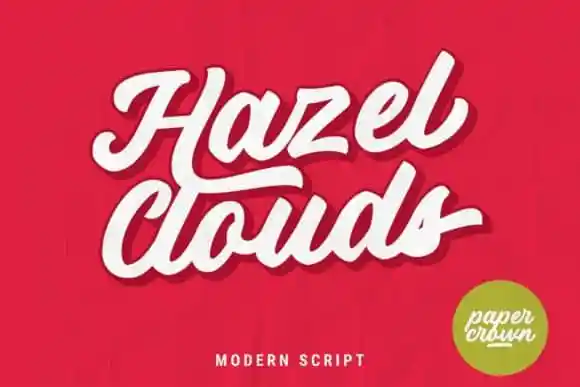
A Hazel Clouds Script Font é uma seleção única de letras decorativas que surgiu do cruzamento entre a arte manual de letra escrita e a tipografia. Feitas à mão, estas letras são perfeitas para quem busca um estilo elegante e sofisticado em suas criações digitais. Elas permitem criar textos fluidos e artísticos, idealmente para anúncios ou design gráfico que exija uma escrita criativa e diferenciada. Suas linhas arredondadas e harmonias sutis fazem da Hazel Clouds Script Font um recurso valioso para designers em busca de uma fonte que ofereça flexibilidade e originalidade. Esses designs foram projetados especificamente para criar textos atraentes, que podem complementar qualquer projeto de design gráfico moderno. Esta fonte é um must-have para quem procura expressar criatividade através do texto digital, proporcionando aos designers uma maneira única de destacar suas criações. É perfeita para designers gráficos, anúncios digitais ou até mesmo o layout de sites web, oferecendo a opção de adicionar um toque delicado e distinto à qualquer projeto.